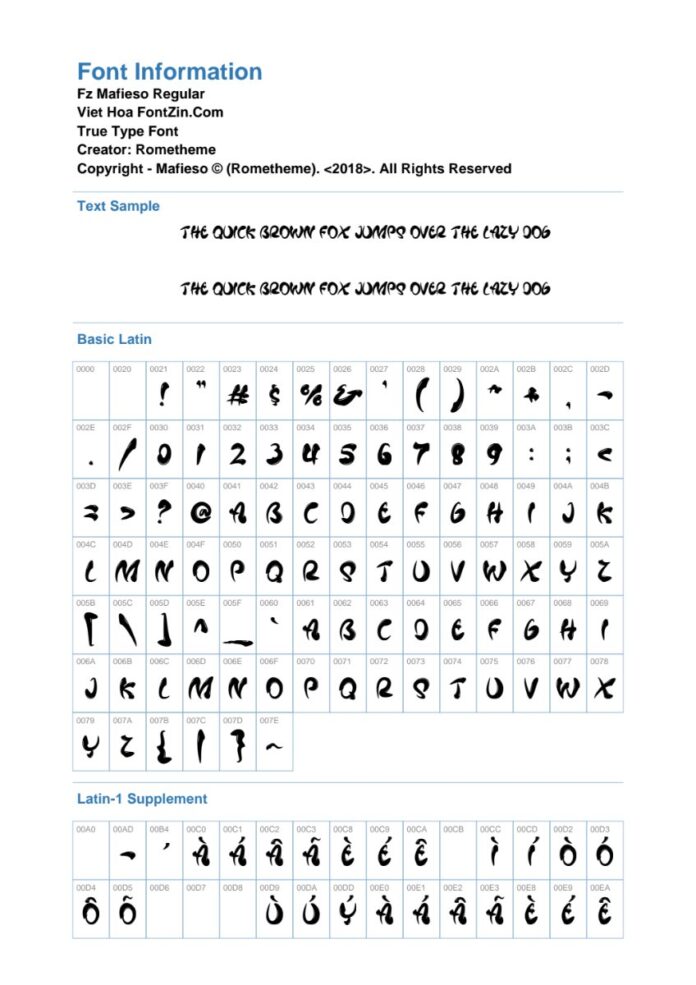
Font Fz Mafieso Việt Hóa Độc Đáo. Khám phá Font Fz Mafieso Việt Hóa, một lựa chọn tuyệt vời cho thiết kế sáng tạo. Với phong cách viết tay độc đáo, font này phù hợp cho nhiều dự án từ quảng cáo đến trang trí, mang lại vẻ đẹp tự nhiên và cá tính.
Giới thiệu Font Fz Mafieso Việt Hóa
Font Fz Mafieso là một kiểu chữ script (viết tay) với những nét vẽ phóng khoáng, tự nhiên và đầy cá tính. Được thiết kế bởi Rometheme, font chữ này mang đến một cảm giác thủ công, gần gũi nhưng không kém phần chuyên nghiệp. Phiên bản Việt Hóa của Fz Mafieso tại Poster.vn đảm bảo rằng bạn có thể sử dụng đầy đủ các ký tự tiếng Việt, bao gồm cả dấu và các ký tự đặc biệt, mà không gặp bất kỳ lỗi hiển thị nào.
Đặc điểm nổi bật của Font Fz Mafieso
- Phong cách độc đáo: Fz Mafieso nổi bật với những nét chữ không đều, tạo cảm giác như được viết bằng tay một cách ngẫu hứng nhưng vẫn giữ được sự hài hòa.
- Việt Hóa hoàn chỉnh: Toàn bộ các ký tự tiếng Việt đã được tối ưu, giúp bạn dễ dàng áp dụng vào các thiết kế dành cho thị trường Việt Nam.
- Tính ứng dụng cao: Phù hợp với nhiều loại hình thiết kế khác nhau, từ tiêu đề, logo, poster, banner, thiệp mời cho đến các ấn phẩm truyền thông xã hội.
- Tạo điểm nhấn: Với sự phá cách trong từng nét chữ, Fz Mafieso dễ dàng thu hút sự chú ý và tạo điểm nhấn mạnh mẽ cho thông điệp của bạn.
Ứng dụng của Font Fz Mafieso trong thiết kế
Font Fz Mafieso Việt Hóa là một công cụ đa năng cho các nhà thiết kế. Dưới đây là một số gợi ý về cách bạn có thể tận dụng font chữ này:
1. Thiết kế logo và branding
Với vẻ ngoài độc đáo và cá tính, Fz Mafieso là lựa chọn lý tưởng để tạo ra các logo mang đậm dấu ấn riêng. Nó đặc biệt phù hợp với các thương hiệu muốn truyền tải sự sáng tạo, nghệ thuật hoặc phong cách thủ công.
2. Ấn phẩm quảng cáo và truyền thông
Sử dụng Fz Mafieso cho tiêu đề của poster, banner, flyer hoặc các bài đăng trên mạng xã hội để thu hút sự chú ý. Font chữ này sẽ giúp thông điệp của bạn trở nên nổi bật và dễ nhớ hơn.
3. Thiệp mời và thiệp chúc mừng
Khi thiết kế thiệp cưới, thiệp sinh nhật, hoặc thiệp chúc mừng các dịp lễ, Fz Mafieso sẽ mang lại vẻ đẹp lãng mạn, bay bổng và cá nhân hóa cho từng tấm thiệp.
4. Thiết kế bao bì sản phẩm
Nếu bạn đang thiết kế bao bì cho các sản phẩm thủ công, thực phẩm tự nhiên, hoặc các mặt hàng có yếu tố nghệ thuật, Fz Mafieso có thể giúp tạo ra một vẻ ngoài chân thực và hấp dẫn.
5. Trang trí nội thất và decal
Font chữ này cũng có thể được sử dụng để tạo ra các câu trích dẫn truyền cảm hứng, decal dán tường hoặc các yếu tố trang trí khác, mang lại phong cách độc đáo cho không gian sống và làm việc.
Font Fz Mafieso có hỗ trợ tiếng Việt không?
Có, Font Fz Mafieso tại Poster.vn đã được Việt Hóa hoàn chỉnh, hỗ trợ đầy đủ các ký tự tiếng Việt có dấu.
Font Fz Mafieso phù hợp với loại hình thiết kế nào?
Font này rất phù hợp cho logo, tiêu đề, poster, banner, thiệp mời, bao bì sản phẩm và các thiết kế cần sự độc đáo, cá tính và phong cách viết tay.